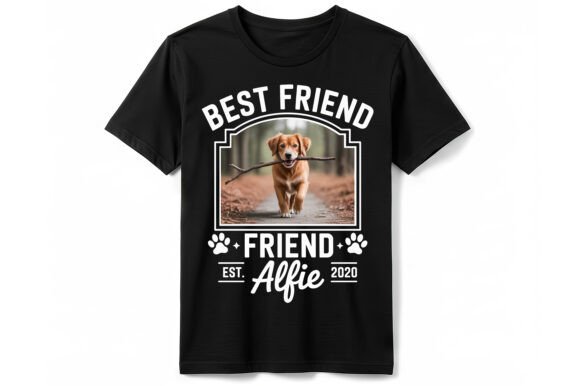
Alfie Best Friend T-Shirt
找到合适的设计元素可能具有挑战性,但 Alfie Best Friend T-Shirt 提供了一系列出色的藏品,可瞬间提升您的作品质量。
无论您是创建 POD(按需打印)产品、婚礼邀请函还是社交媒体图形,Alfie Best Friend T-Shirt 都是理想的选择。